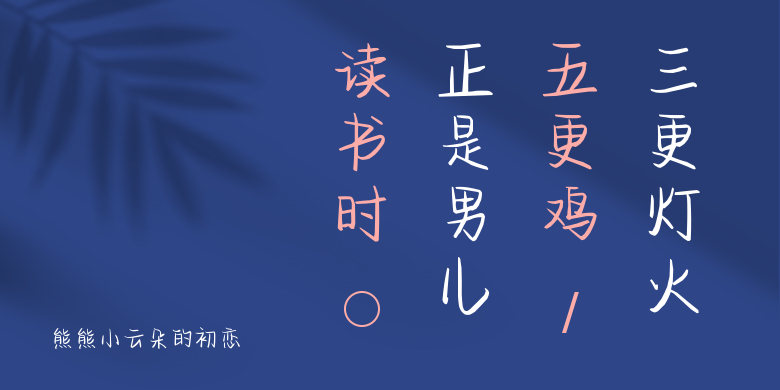
熊熊小云朵的初恋
熊熊小云朵的初恋,这款字体结构工整、笔画清晰,兼顾美观与易读性,适用于标题、正文、海报、包装、LOGO 等多种场景。字形优雅稳定,风格百搭耐看,适配日常排版与创意设计,让文字呈现更舒适、更具质感。熊熊小云朵的初恋一笔一画,皆是细节,以均衡的比例、流畅的线条打造舒适视觉体验,字形端正大气,风格简约现代。无论是商业设计、品牌宣传还是日常排版,都能轻松驾驭,让文字更有格调与力量。熊熊小云朵的初恋字体下载。